Gaya font script seringkali digunakan untuk menciptakan kesan desain yang elegan, mewah, dan feminim. Namun ada banyak gaya desain font script tidak hanya yang elegan, tetapi juga ada yang ramah hingga playful. Setiap gaya font script dapat mewakili karakter berbeda dalam desain logo berbeda dengan font berbeda.
Gaya font script yang seperti tulisan tangan akan terlihat mengalir dan alami, namun ketebalan, gaya tulisan, hingga bentuk huruf dapat memengaruhi kesan yang disampaikan. Font script dapat memiliki berbagai gaya huruf dari yang elegan, formal, dan menyenangkan. Pemilihan font script dalam desain logo umumnya karena kemampuannya menyampaikan emosi, kepribadian, dan visual yang estetis.
Analisis Perbedaan Gaya Font Script dan Kesannya
Desain logo modern yang menggunakan font script akan memilih gaya font yang bersih dan halus agar menciptakan logo minimalis. Jika memiliki garis tipis, maka font script akan membuat desain tampil elegan dan feminim. Berbeda lagi jika memiliki garis tebal dan melengkung, perhatikan bagaimana perbedaan style font dalam logo brand berbeda ini:
Logo Srikandi Laundry Self Service
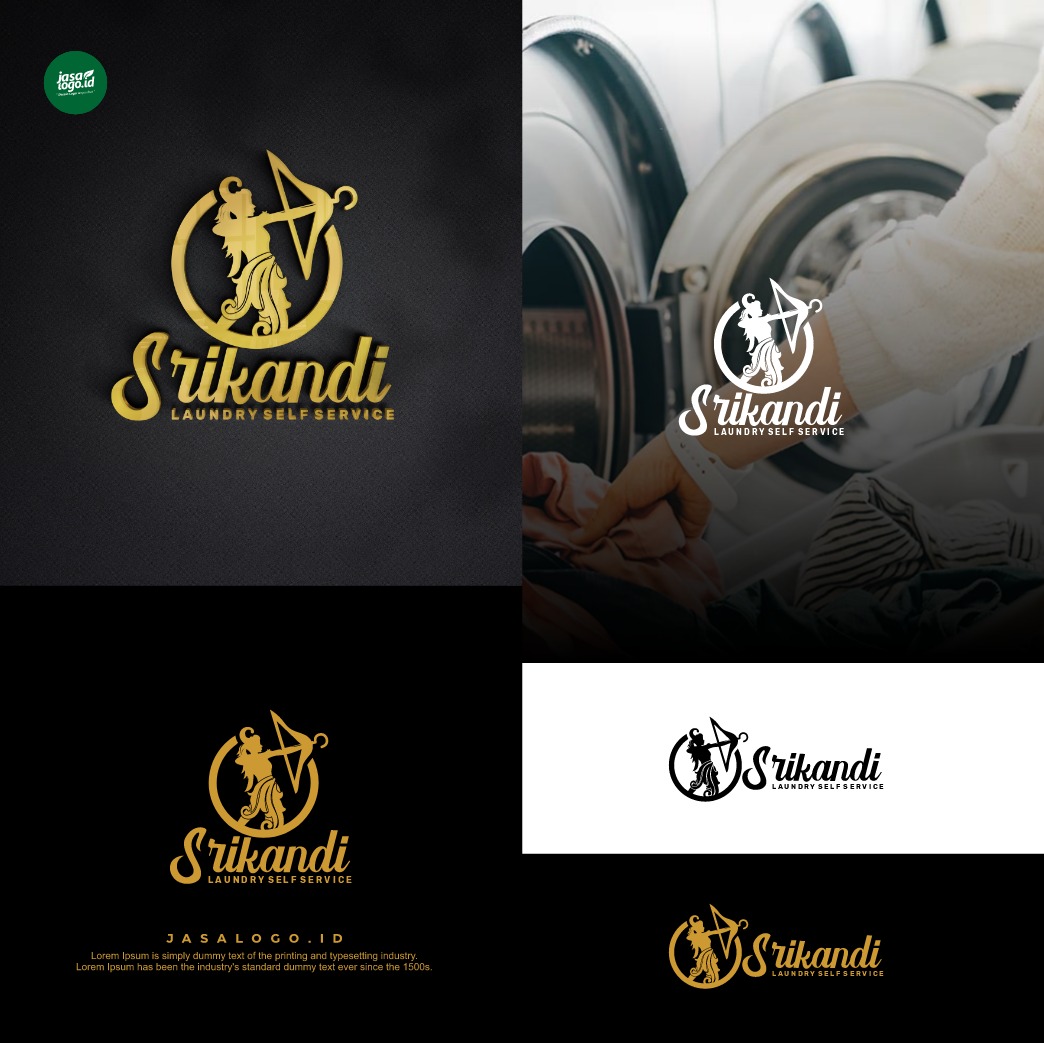
Desain logo untuk bisnis laundry ini menggunakan gaya font script dengan huruf bersambung. Font script memiliki variasi semi dekoratif karena memiliki karena ujung huruf yang seperti ornamen melengkung. Gaya hurufnya agak tebal dan bergelombang sehingga menciptakan kesan:
Elegan dan Berkarakter
Gaya font script yang memiliki huruf bersambung, garis bersih, dan halus menciptakan visual logo elegan. Meski elegan, tetapi juga berkarakter kuat karena memiliki font agak tebal dan dekoratif.
Feminim dan Tangguh
Pemilihan font script yang elegan ini harmonis dengan nama brand yang feminim yaitu srikandi. Gaya font script klasik relevan mewakili citra srikandi dari mitologi klasik yang feminim namun tangguh.
Profesional dan Percaya Diri
Brand laundry dengan style logo klasik tampil profesional karena gaya font script formal yang digunakan. Style font ini cocok untuk brand jasa cepat dan sigap, namun memiliki sentuhan tradisional.
Logo Ngopi Santai Antikorupsi
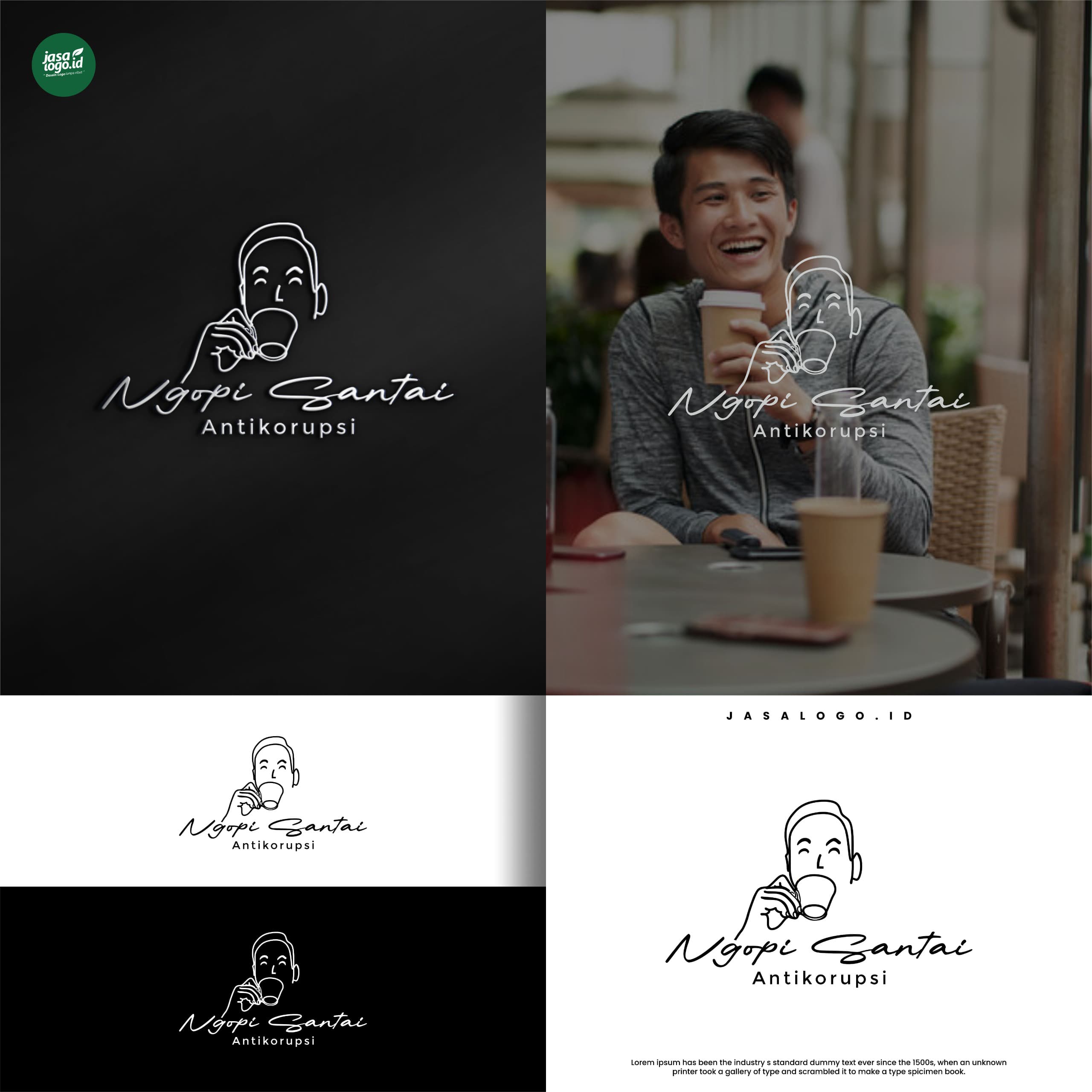
Desain logo bisnis kopi memiliki style logo line art yang tipis membentuk orang minum kopi dan memiliki font script tipis. Font script dalam logo ini memiliki gaya huruf kasual yang menyerupai tangan sehingga terlihat alami. Garis tipis, huruf bersambung, dan bersih menciptakan kesan seperti:
Menciptakan Kesan Santai dan Akrab
Daripada font script pada logo sebelumnya, logo ini memiliki gaya huruf yang lebih kasual mirip tulisan tangan yang agak berantakan. Gaya huruf script kasual ini membuat brand kopi berkesan santai dan akrab.
Memberi Kesan Tempat Nongkrong dan Membangun Komunitas
Sesuai dengan nama dan gaya font script kasual yang digunakan, font ini membuat brand kopi mewakili kesan komunitas dan tempat nongkrong yang santai. Brand kopi dengan font kasual akan merepresentasikan, keterbukaan, dan humanis.
Logo Havelle
Desain logo untuk brand sepatu ini memiliki gaya minimalis dengan ikon datar dan font script tipis. Font script dalam logo ini bergaya modern, halus, dan ramping, sehingga menciptakan kesan feminim. Berbeda dengan font tipis kasual, font script ini memiliki visual elegan dan feminim, yang menciptakan kesan brand seperti:
Fashionable, Elegan, dan Canggih
Brand fashion termasuk sepatu ini cocok menggunakan gaya font script yang elegan dan feminim. Font script ramping dan bergaya modern ini memberi kesan fashionable dan canggih.
Berkesan Ringan, Stylish, dan Relevan untuk Brand Mode
Font tipis akan menciptakan kesan minimalis serta membuat logo tampak ringan namun masih stylish. Gaya font script tipis yang elegan dan feminim ini cocok untuk brand mode sepatu.
Logo Foyn Beauty Care
Style font script dalam logo skincare ini memiliki gaya huruf bersambung dengan garis kontras serta memiliki visual yang bersih. Gaya font script dengan sapuan halus dan garis melengkung lembut menciptakan kesan logo modern yang elegan. Style font script elegan ini cocok untuk brand kecantikan, untuk menciptakan kesan:
Berkesan Lembut, Anggun, dan Perawatan Diri
Gaya font script ini memiliki gaya huruf yang halus dan bersih sehingga membuat brand skincare memiliki kesan lembut. Font script elegan tampak cocok untuk mewakili brand perawatan diri yang anggun.
Memberi Kesan Tenang dan Terpercaya
Gaya font modern ini cocok untuk membangun citra produk skincare yang memberi ketenangan. Style font modern tampak bersih dan mudah dibaca sehingga bisa merepresentasikan kesan produk terpercaya dan berkualitas.
Logo Flower Pilates Studio
Desain logo untuk bisnis pilates ini menggunakan gaya font script untuk mencerminkan brand pilates yang anggun dan elegan. Gaya font script dalam logo ini memiliki style font klasik dan artistik. Garis halus dan melengkung dalam logo bisnis ini mewakili seni dan gerak tubuh.
Font script yang memiliki visual seperti tulisan tangan akan relevan untuk menyampaikan karakter dan identitas brand dengan baik. Setiap gaya font script dengan gaya huruf kasual, tipis, tebal, dan melengkung akan menciptakan kesan berbeda dan cocok untuk industri berbeda. Gaya font script yang berbeda akan mampu menciptakan kesan dan makna brand yang sangat spesifik, untuk itu penting memahami karakter brand.